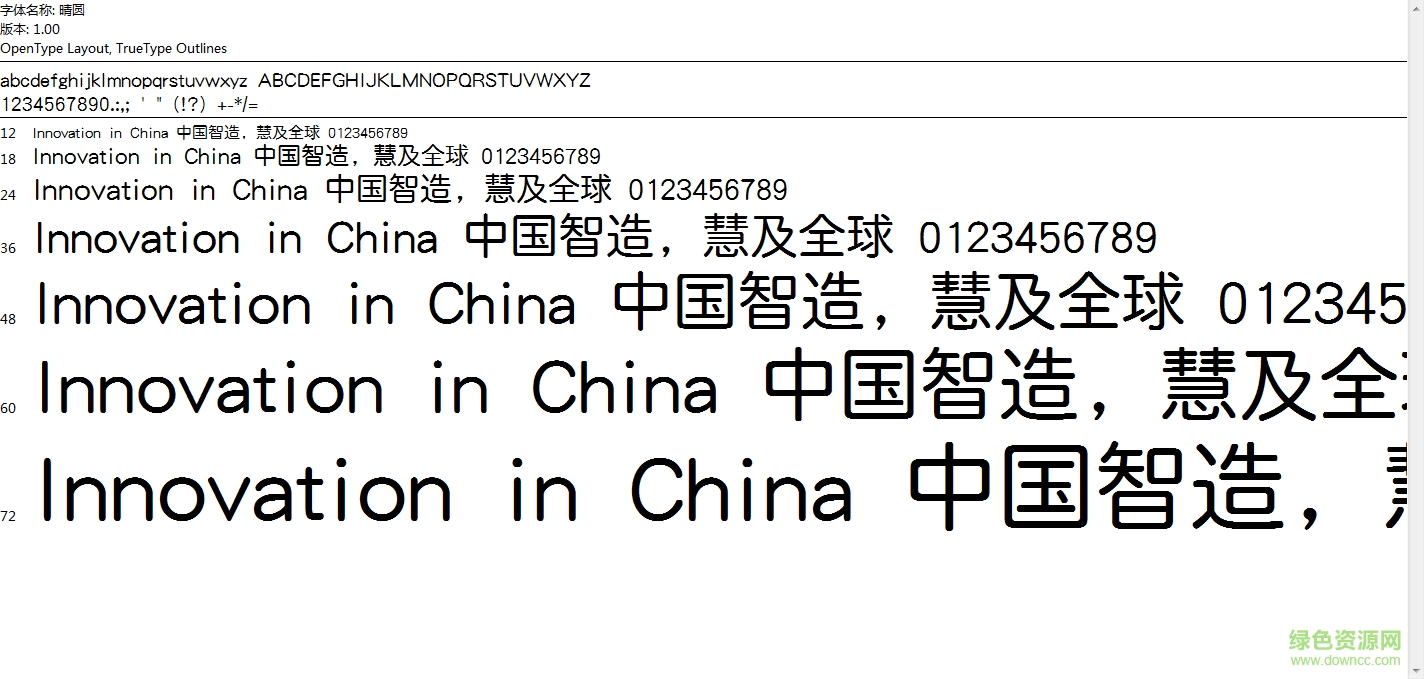
晴圓等寬字體是一款非常美觀的win字體,該字體字型圓潤(rùn),具有翩若驚鴻、鳶飄風(fēng)泊、美女簪花等特點(diǎn),可直接導(dǎo)入至ps中,廣泛的應(yīng)用于廣告設(shè)計(jì)海報(bào)設(shè)計(jì)、影視影像等領(lǐng)域,喜歡的朋友歡迎來(lái)綠色資源網(wǎng)下載!